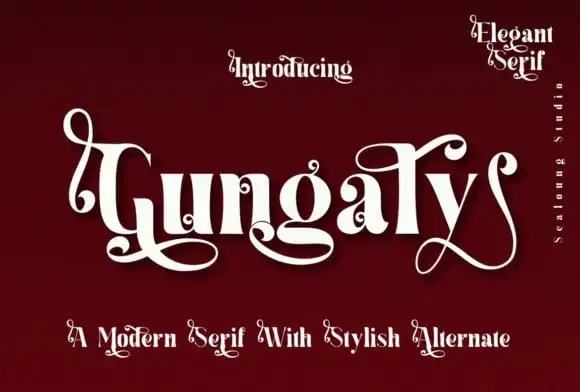
A Gungaly Serif é uma elegante escolha para designers que buscam dar um toque sofisticado aos seus projetos digitais. Essa fonte serif apresenta letras maiúsculas, números e uma grande variedade de pontuação, todas sob um estilo moderno inspirador. Criada pela Sealoung, esta fonte traz um ar elegante às suas ideias de design, tornando-a perfeita para quem busca dar um toque único e atual aos seus projetos. Seja para textos longos ou designs gráficos minimalistas, a Gungaly Serif oferece uma solução versátil que encanta pela sua sofisticação e modernidade. Combinada com a elegância da tipografia serif clássica, ela adiciona um toque especial ao seu design, tornando-a uma fonte ideal para quem busca uma referência visual atualizada no mundo da marca digital.